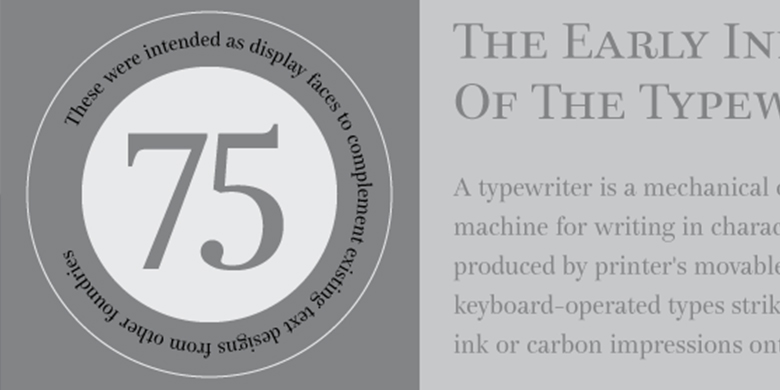
阿根廷设计师Eduardo Manso于2003年创作了Bohemia字体家族。Bohemia巧妙而优雅的本质彰显出精致的字母,从而唤起了像Baskerville这样的过渡风格字体,虽然大多数类似Baskerville的设计往往不像Manso那样曲线优美!Bohemia以较小的文本尺寸(例如9pt及以上)显示时表现最突出,同时仍保持独特的个性和活力。Bohemia是文本字体的一个相当不错的选择。
评论家一直对此赞不绝口。2003年,Bohemia通过第四届国际字体设计大赛(ITDC)进入Linotype,并斩获三项最高奖项之一。2004年,该字体以Argot的名称获得纽约字体设计指导俱乐部(Type Directors Club of New York)的Certificate of Excellence in Type Design奖。Bohemia还入选了2004年在捷克共和国布尔诺市举办的第21届国际图形设计双年展,后来在Bienal Letras Latinas 2004展览中被选为最相关的作品之一,该展览在布宜诺斯艾利斯、圣保罗、圣地亚哥和维拉克鲁兹巡回展出。”
Argentinean designer Eduardo Manso created the Bohemia type family in 2003. Bohemia’s cunning and elegant essence shows off refined letters that evoke the Transitional style typefaces like Baskerville, though most Baskerville-like designs tend not to be as curvaceous as Manso’s! True to form, Bohemia shines in smaller text sizes, like 9 point and above, while still maintaining a unique character and spirit. Bohemia is a great alternative to better-known text faces.
The critics have been raving. Bohemia came to Linotype via its fourth International Type Design Contest (ITDC) [Link] in 2003, where it received one of the three top awards. Under the name Argot, this typeface received a Certificate of Excellence in Type Design from the Type Directors Club of New York in 2004. Bohemia was also selected for inclusion in the 21st International Biennale of Graphic Design 2004 in Brno, Czech Republic, and was later named one of the most relevant works in the Bienal Letras Latinas 2004 exhibition, which traveled through Buenos Aires, San Paolo, Santiago, and Vera Cruz."